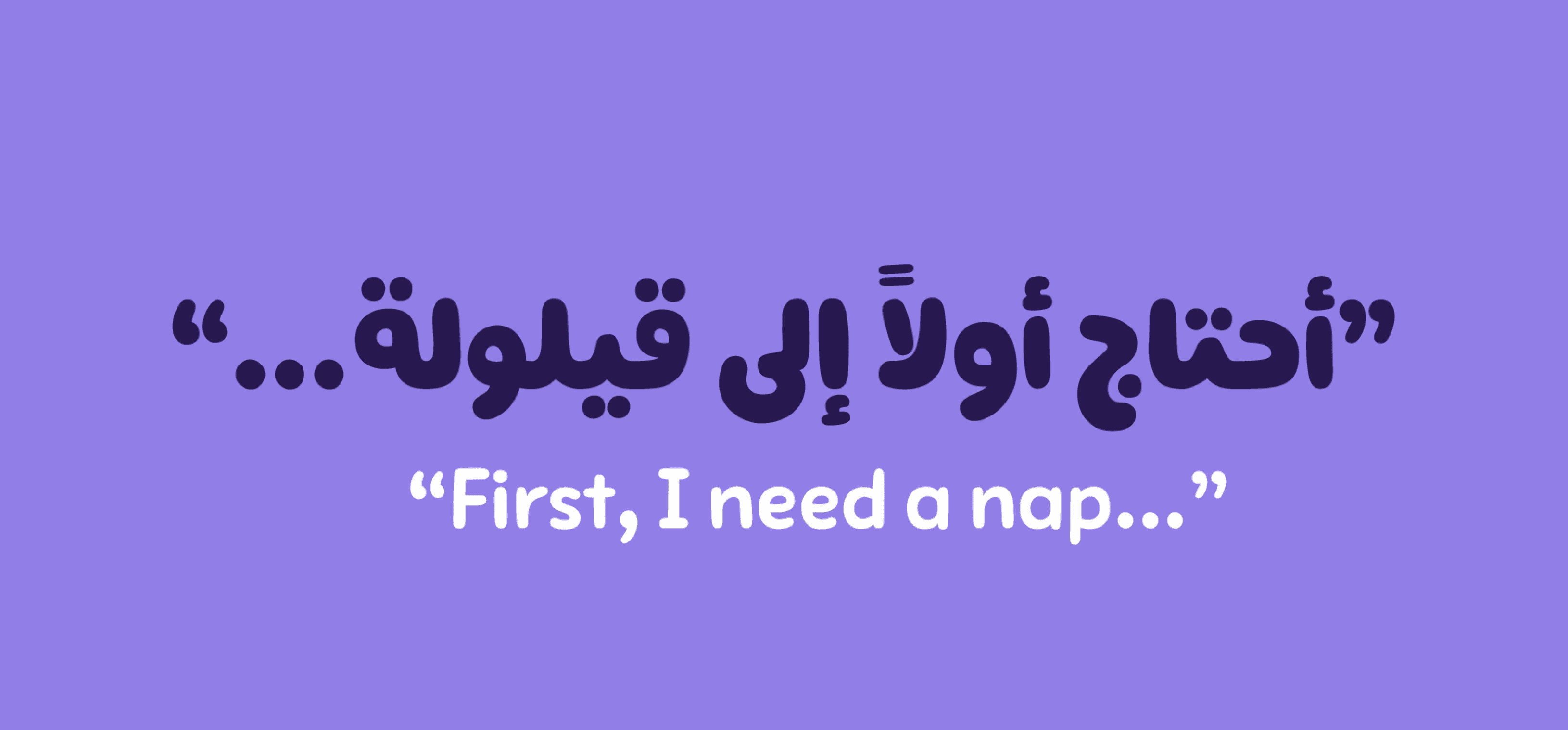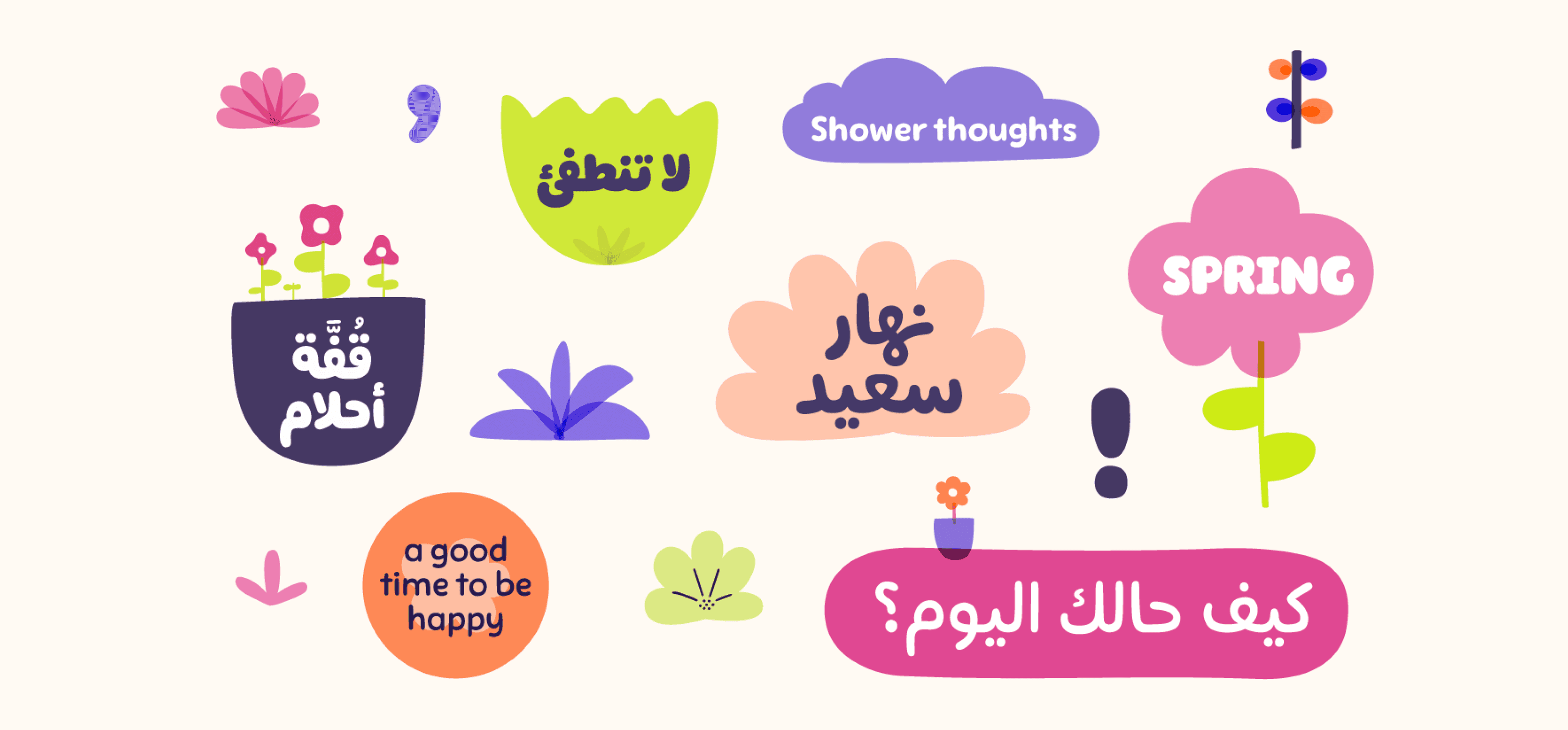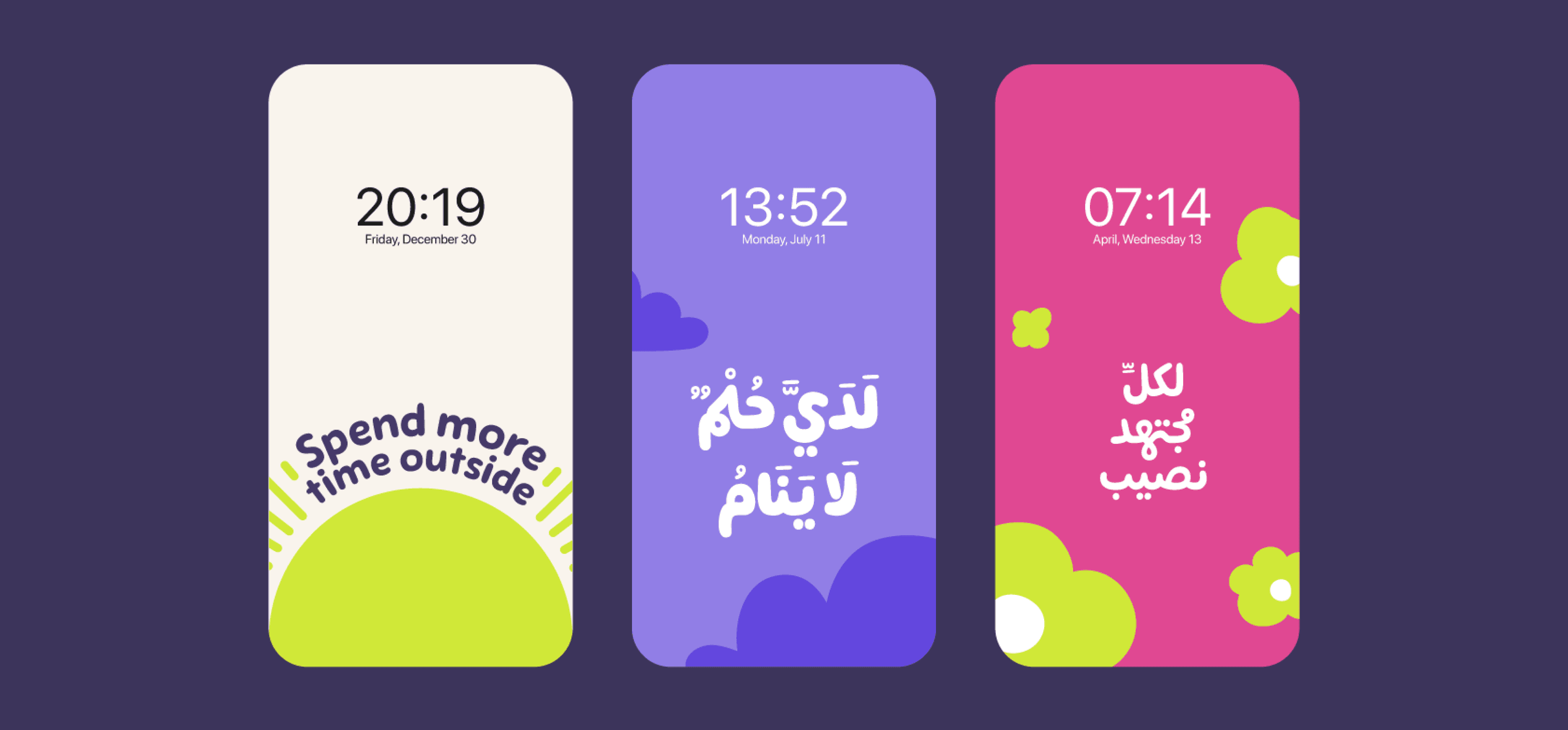
ربيع خط يدويّ يُضفي لطافة على مشاريع التصميم بفضل انحناءات أطرافه ونعومته. يحتوي الخط على أكثر من ٣٠٠ محرف مقرون مما يضيف اتصالات طبيعية بين الأحرف، ويجعل الخط يبدو كخط مرسومٍ يدويًا. ربيع خط متغير بأوزان تتدرج من الوزن الرفيع إلى الغليظ لمساعدة المصمم على تنسيق واختيار الوزن حسب الحاجة. هذا الخط مليء بالحب والوديَّة التي تناسب أنواعًا شتى من مشاريع التصميم؛ مثل تصميم العلامات التجارية والشعارات وكتب الأطفال والقرطاسية.